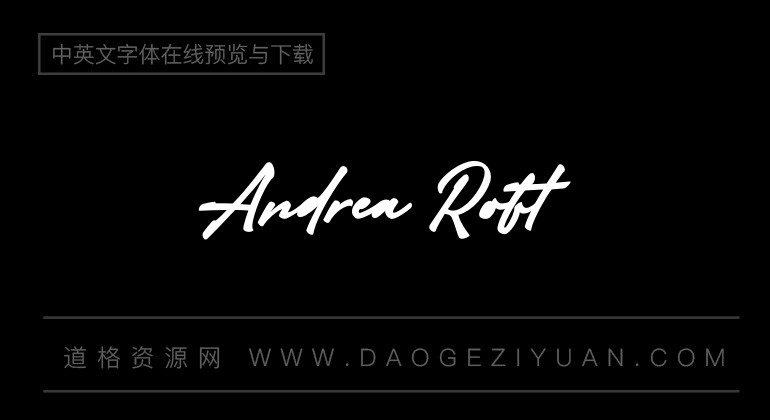
Andrea Roft 字体是一种现代脚本字体,由著名的西班牙设计师Andrea Roft设计。它具有柔和的轮廓、活泼的笔画和优雅的细节,可以为您的设计提供精致的外观。它可以用于现代海报、标志、名片等设计,也可以用于婚礼、邀请函、标题等。Andrea Roft字体具有独特的外观,可以让您的设计更加引人注目。内容介绍
Andrea Roft是一款非常不错的手写艺术字体,具有很好的视觉感,适合于文化类的宣传设计、商业类品牌的广告和产品包装设计以及个性化文字排版等较多场景。